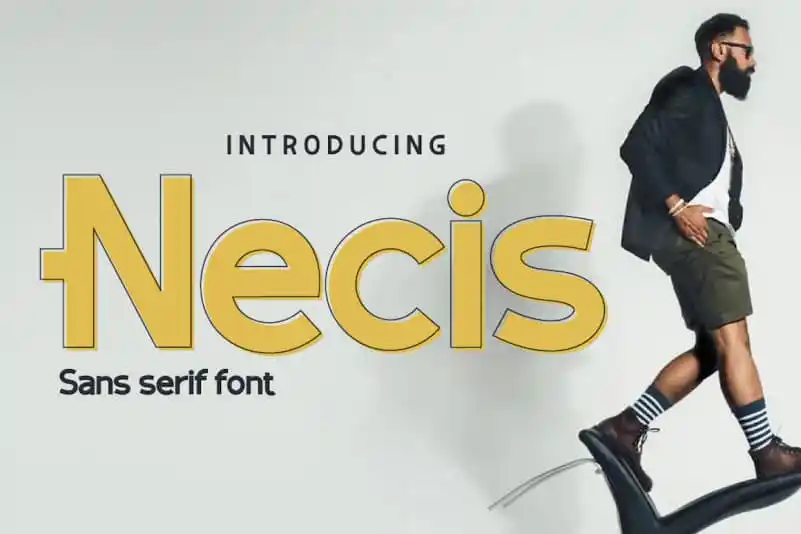
Necis Sans Serif Font – Download Grátis
Necis Sans Serif é uma fonte sans-serif projetada com linhas agradavelmente curvas e elementos geométricos que adicionam um toque único. Este design simples e elegante oferece um aspecto limpo e moderno, mas também traz um toque desconcertantemente divertido à alternativa. O uso de letras maiúsculas em Necis Sans Serif é especialmente útil para assinalar seu nome ou título de marca, enquanto as várias opções disponíveis fornecem a perfeita forma de adicionar elegância quando necessário. Esta fonte é uma ótima escolha para designers e estilistas que desejam um look moderno e arredondado, sem perder o caráter distintivo da tipografia geométrica.